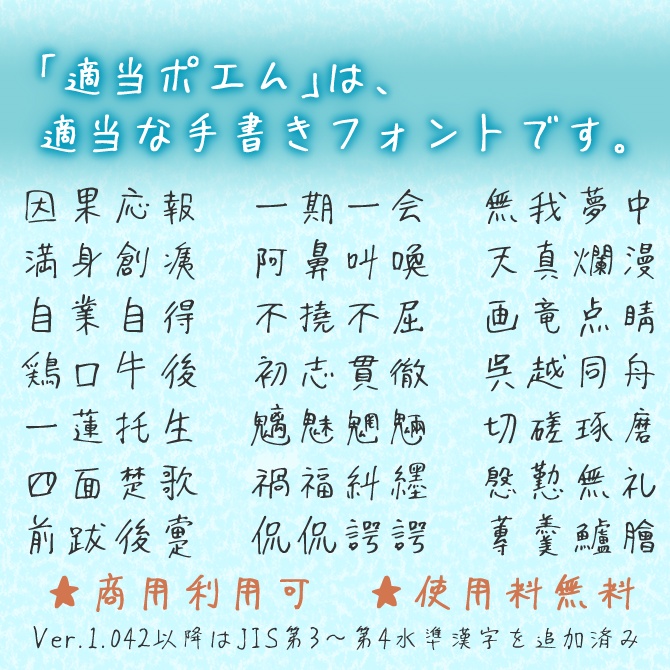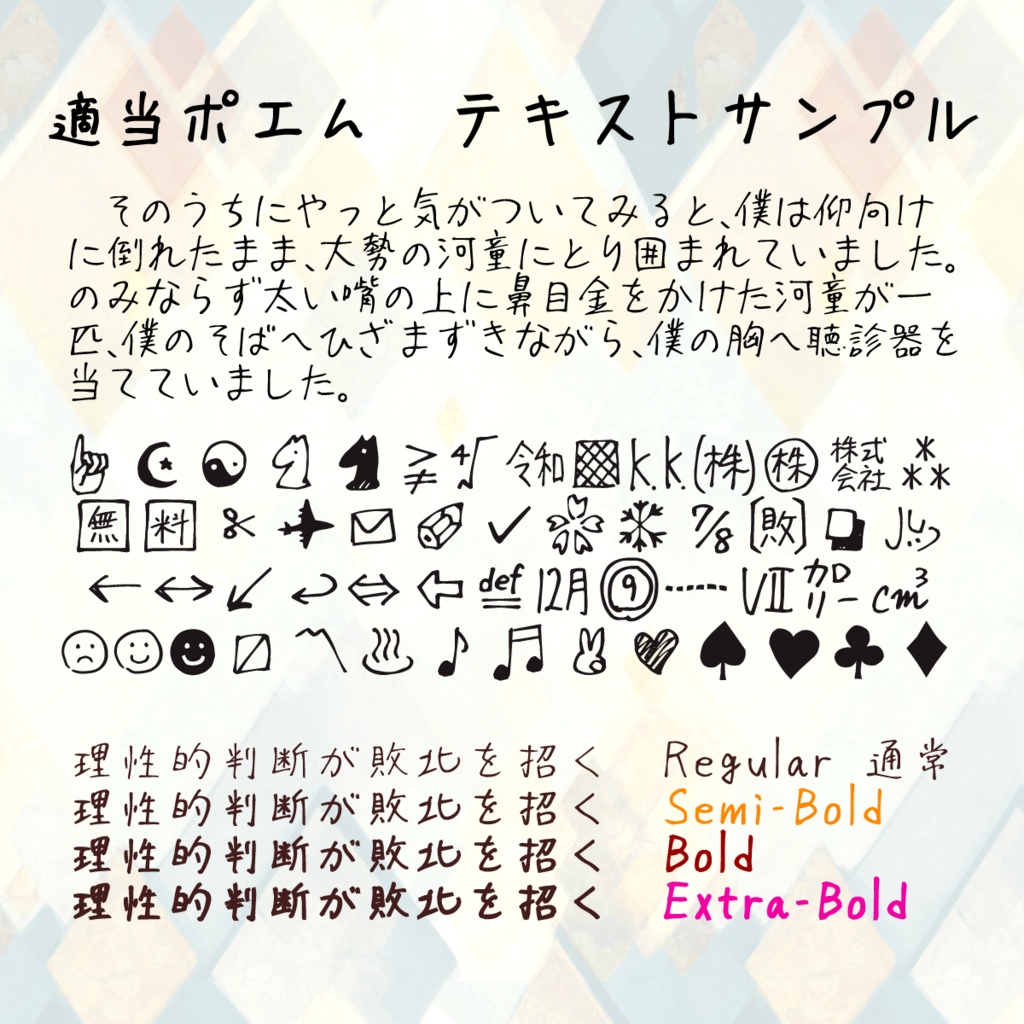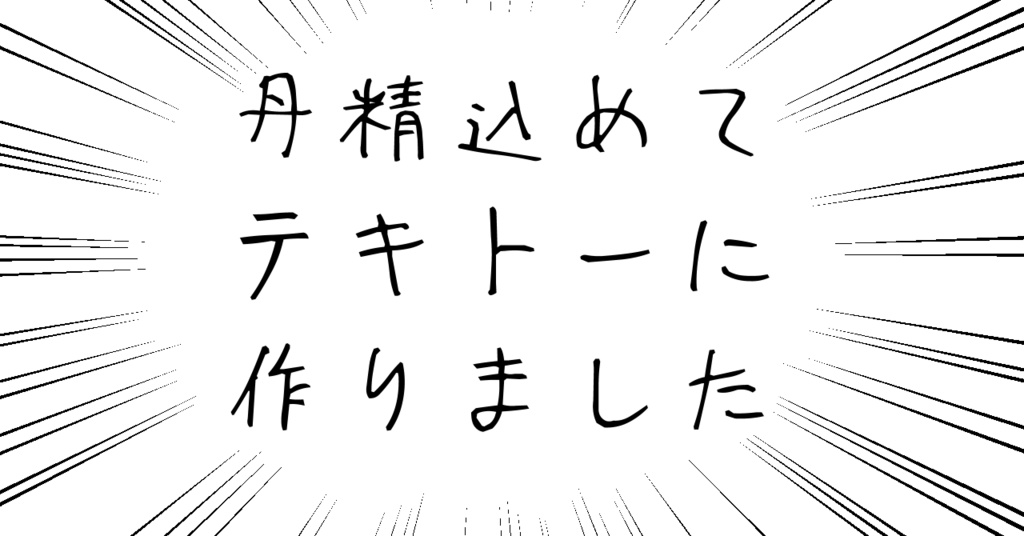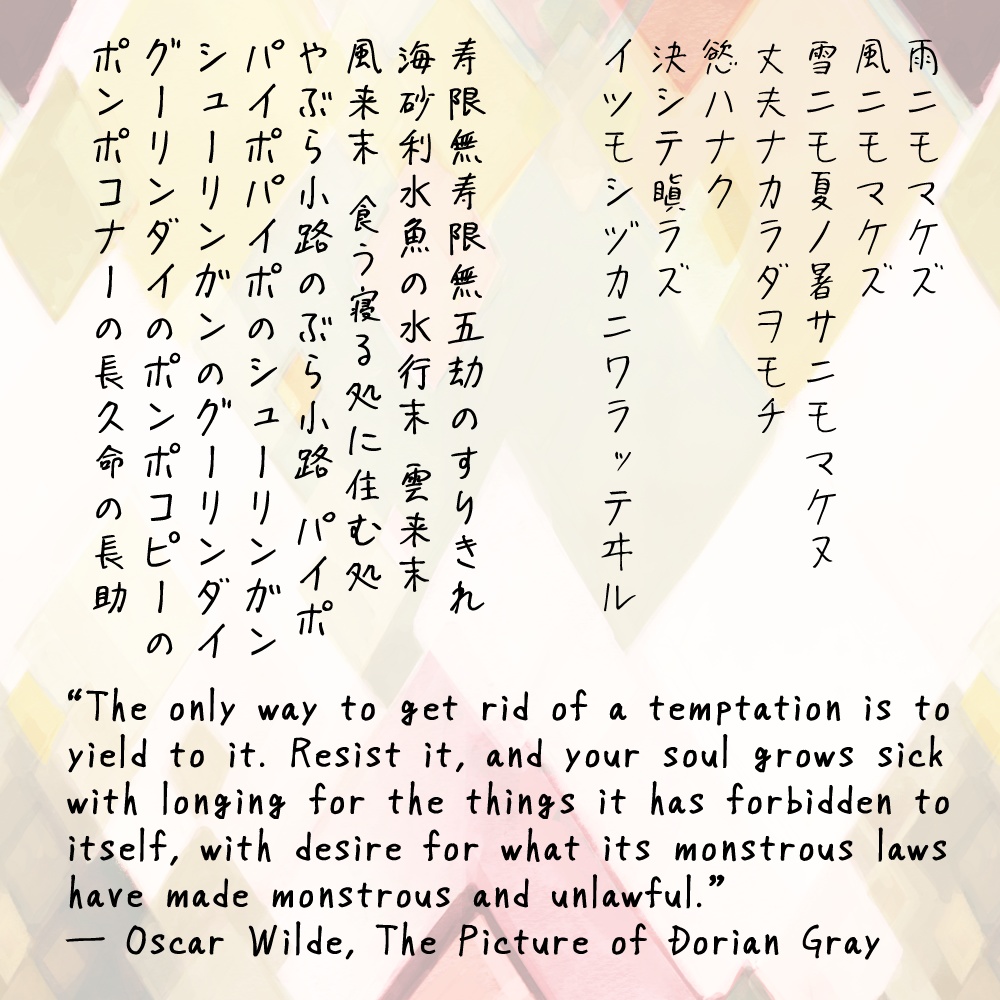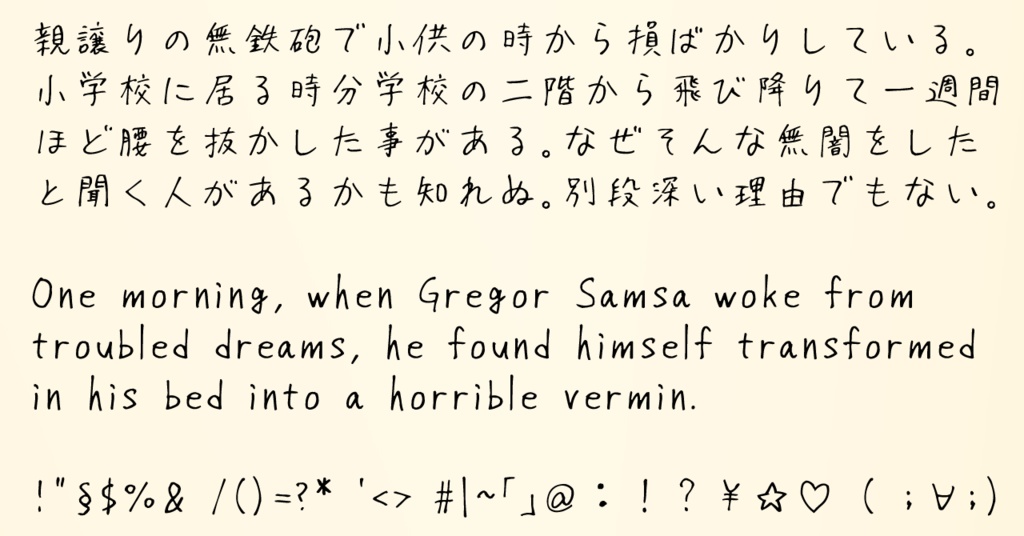
適当ポエム(フリーフォント)
リアルな筆致とインク溜まりが特徴の日本語フォントです。 英数字、ひらがな、カタカナ、JIS第1~4水準漢字を含む約16100字を収録しています。 ゲーム、イラスト、動画、印刷物など、さまざまな用途に利用できます。 文字の大きさや丁寧さにばらつきがあります。 アップデートにより文字追加や誤字修正、微調整を行っています。
TekitouPoem.ttf が通常版です。 太さが違うバージョンを作ってみました。中太(Semi-Bold)、太字(Bold)、特太(Extra-Bold)です。機械的に太くしただけなので、細かい字は潰れます。ご了承ください。